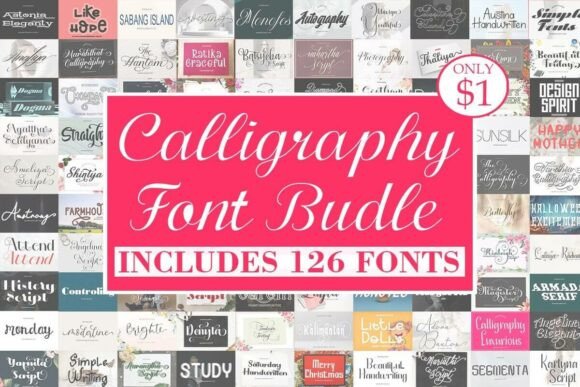
Calligraphy Font Bundle
Trouver les bons éléments de conception peut être un défi, mais Calligraphy Font Bundle propose une collection exceptionnelle qui rehausse instantanément votre travail.
Que vous créiez des produits POD (impression à la demande), des invitations de mariage ou des visuels pour les réseaux sociaux, Calligraphy Font Bundle est un choix idéal.